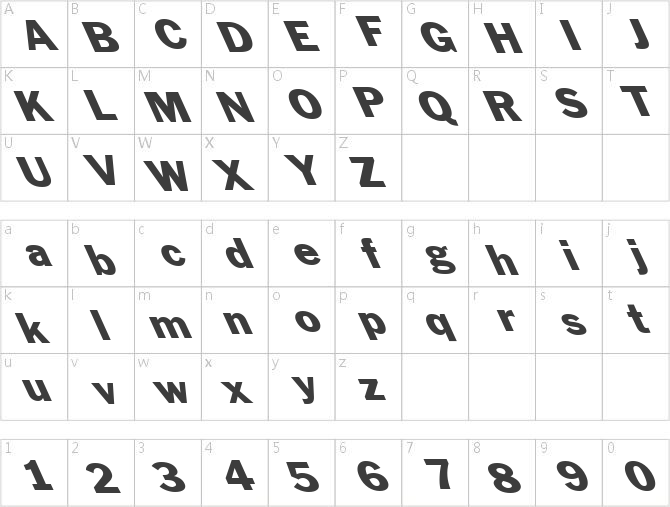
FZ BASIC 56 LEFTY
FZ BASIC 56 LEFTY介紹
FZ BASIC 56 LEFTY字體字庫是一款讓人賞心悅目、百看不厭的英文字體,適合各類廣告和產(chǎn)品包裝設計應用,字體大小0.04MB,格式為ttf字體,上傳用戶是那是不變的,作者/版權方為未知
FZ BASIC 56 LEFTY效果圖